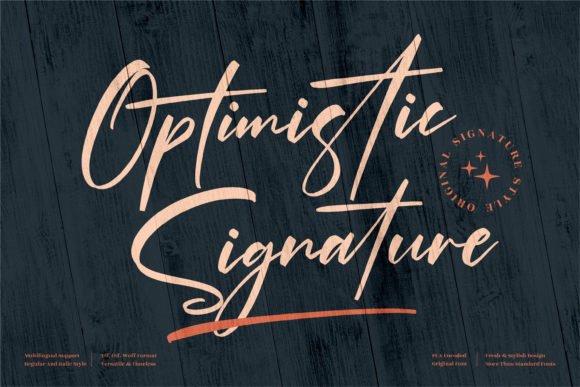
Optimistic Signature
- это шикарный, изысканный шрифт, излучающий утонченность и элегантность.
Стильные чередования и лигатуры делают этот шрифт идеальным вариантом для любого проекта.
Optimistic Signature закодирован в PUA, что означает, что вы можете легко получить доступ ко всем удивительным глифам и лигатурам!